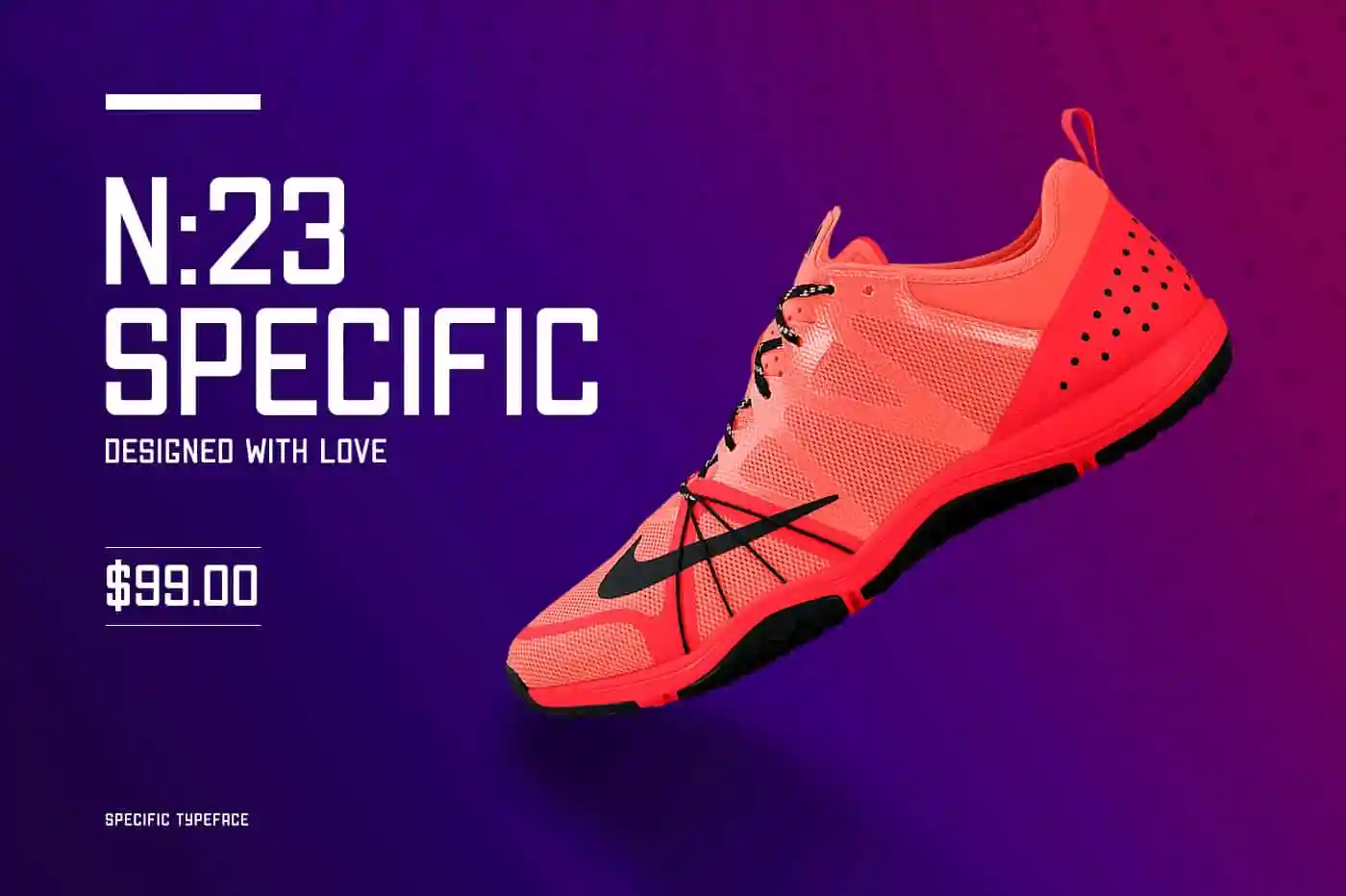
Specific Typeface
Introduzimos a Typeface Specific, uma fonte de sans serif criada pelo designer 178-MC. Esta novidade tem uma estrutura maior dos caracteres maiúsculos em relação às fontes normais, característica que torna-a um recurso ideal para aplicar em diversas mídias. Seus elementos são mais condensados, com linhas arredondadas e quadradas, o que adiciona um toque de modernidade e simplicidade à sua aparência. Ideal para ser usada nos posters, embalagens, anúncios nas revistas e jornais, logotipos, bandeiras, imagens promocionais e uniformes de futebol. Suas linhas retas e clean são um contraponto perfeito à delicadeza dos bordados arredondados que compõe cada caractere, criando uma harmonia única entre o forte e o suave. Com seu design moderno e versátil, a Typeface Specific é uma escolha excelente para os designers digitais em busca de personalidade e estilo. Seja você um designer gráfico experiente ou alguém iniciante, esta fonte oferece flexibilidade suficiente para abranger múltiplas tarefas visuais, tornando-a uma opção valiosa no seu arsenal de ferramentas.